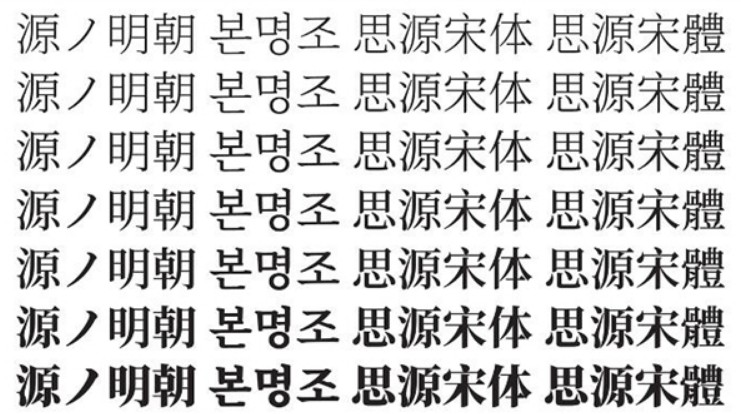
谷歌联合Adobe发布“思源宋体”
新开源字体:谷歌联合Adobe发布“思源宋体”  经过长达1年半的开发之后,Adobe和谷歌于4月3日联合发布了全新开源字体“思源宋体”(Source Han Serif/Noto Serif CJK)。   与此前推出的思源黑体一样,思源宋体以 “SIL开放字体许可证” 开源发行。   官方介绍文档显示,思源宋体包含了简繁日韩四种汉字写法,七种粗细字重,共收录458745个字型,每种字重包括65535个字形。